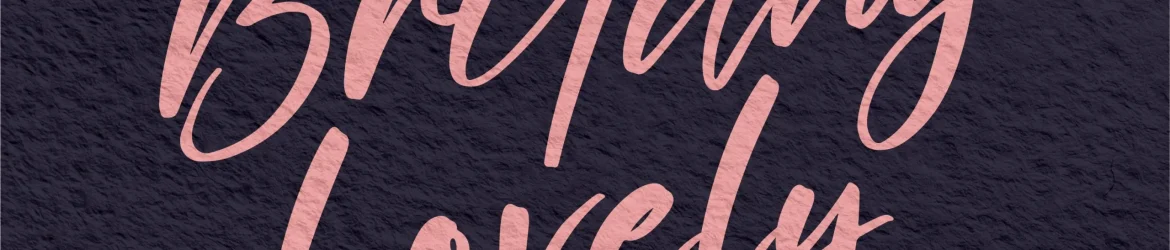
Britany Lovely Font – Download Grátis
A fonte ‘Britany Lovely’ é uma delicada escrita a mão que se destaca por sua simplicidade elegante e versatilidade. Sujeitável a uma variedade de projetos, desde identidades visuais e criações para objetos de decoração até design de embalagens de produtos, este fonte irá enriquecer seu trabalho com um toque autêntico e delicado que se destaca dos demais. Com o designer perspectype responsável pelo seu desenvolvimento, a ‘Britany Lovely’ oferece uma maneira perfeita de adicionar uma dose de personalidade a qualquer projeto. Suas formas leves e suaves tornam-a ideal para criações semelhantes a etiquetas de produto ou capas de livros que precisam de um toque delicado e charmoso. Escolha esta fonte ‘Britany Lovely’ para aqueles momentos em que deseja trazer uma nota delicada aos seus designs, seja para dar vida a suas criações de design gráfico, ilustrações ou mesmo para usar no seu próximo projeto de arte digital. Seja um convite de casamento, uma capa de livro ou até mesmo etiquetas personalizadas, ‘Britany Lovely’ é o ideal que você está procurando.